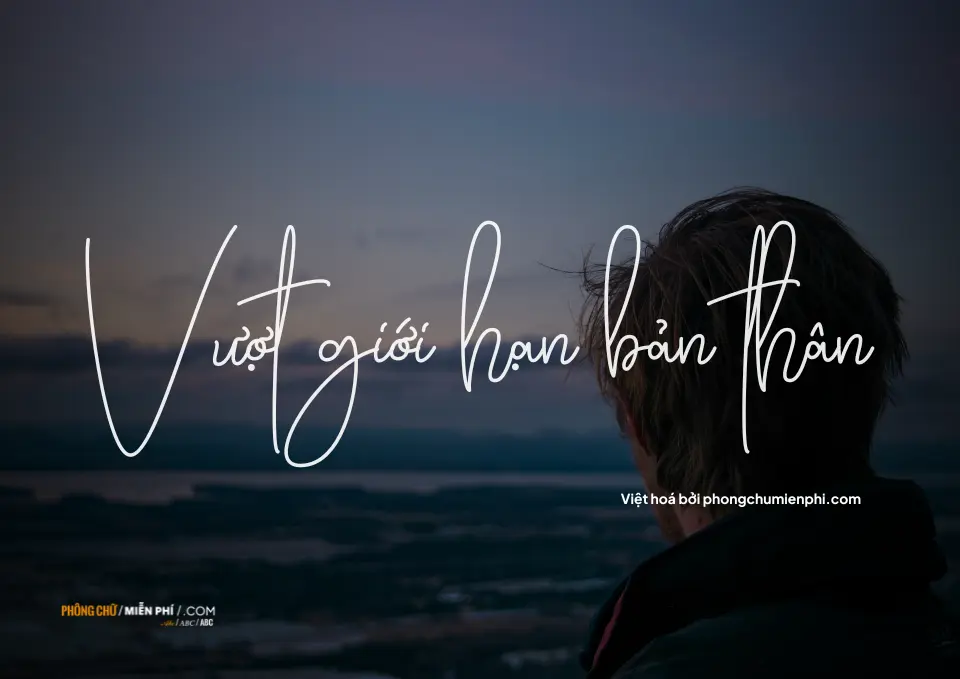
Tên font: Font Việt Hoá DAISUKE REGULAR
Font Việt Hoá PCMP DAISUKE REGULAR
PCMP DAISUKE REGULAR là một phông chữ viết tay nhẹ nhàng, thanh lịch, tràn đầy năng lượng. Nó sẽ mang đến cảm giác độc đáo cho bất kỳ dự án thiết kế nào.